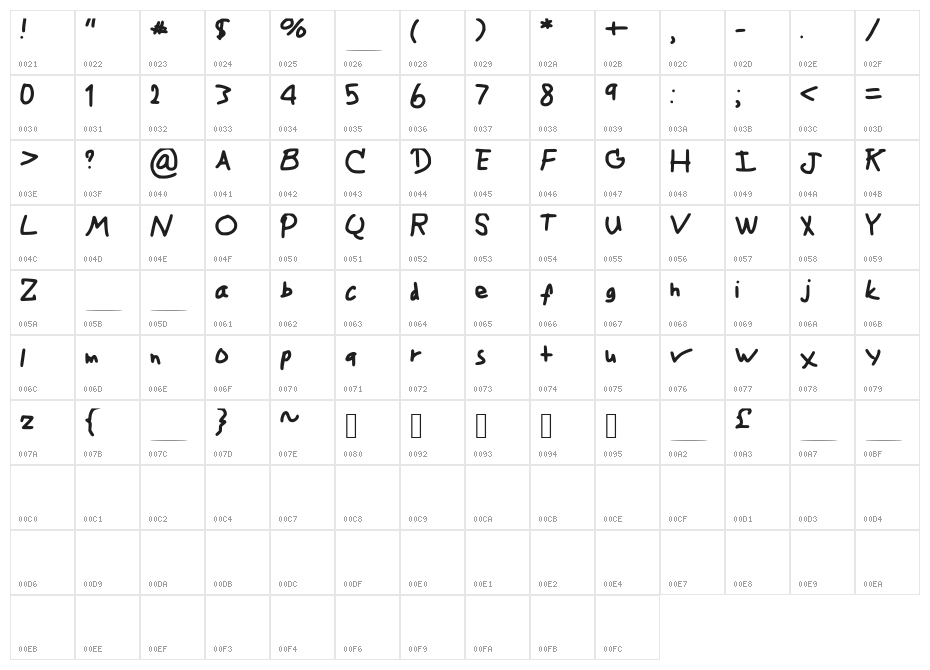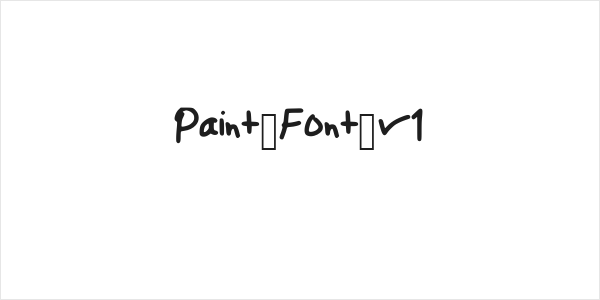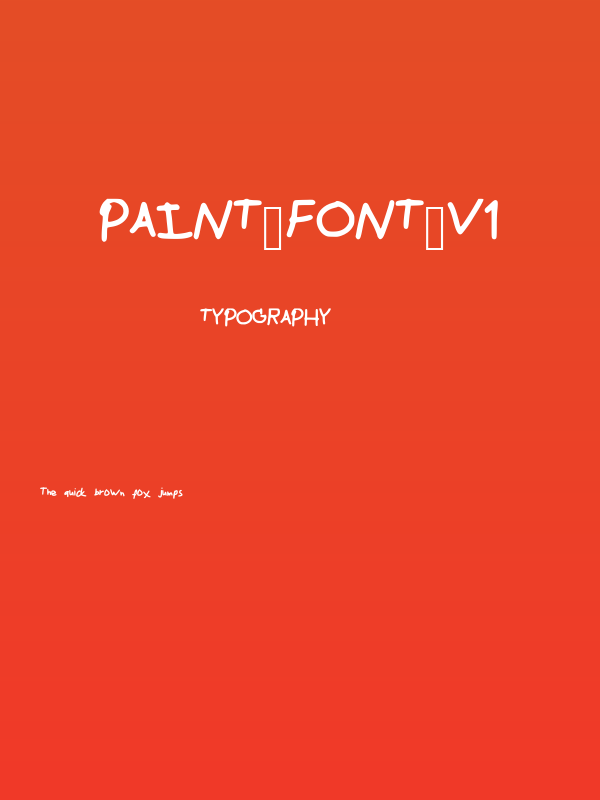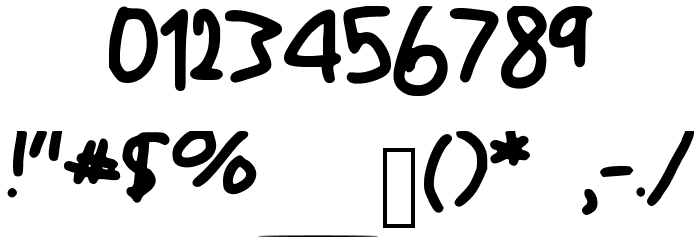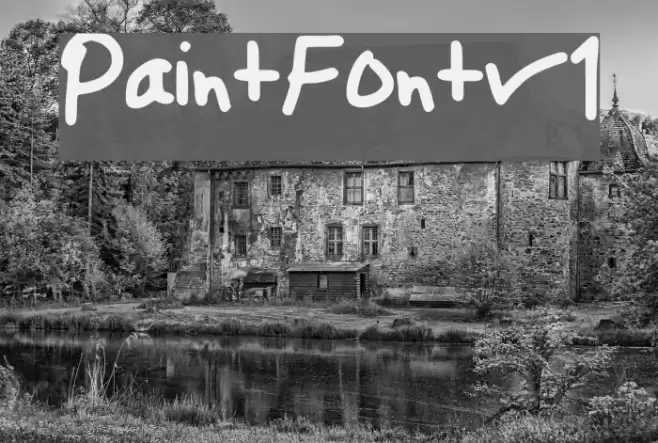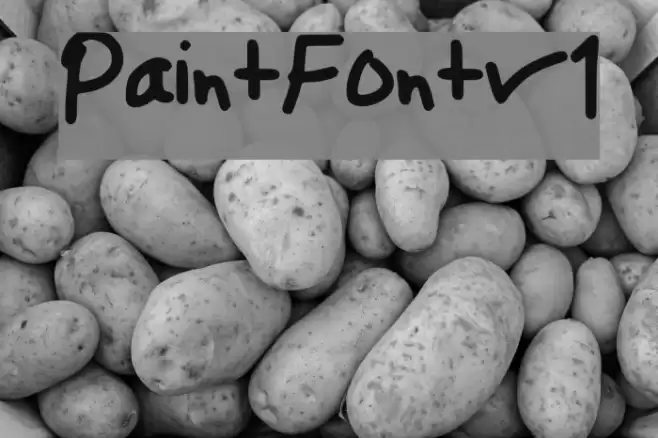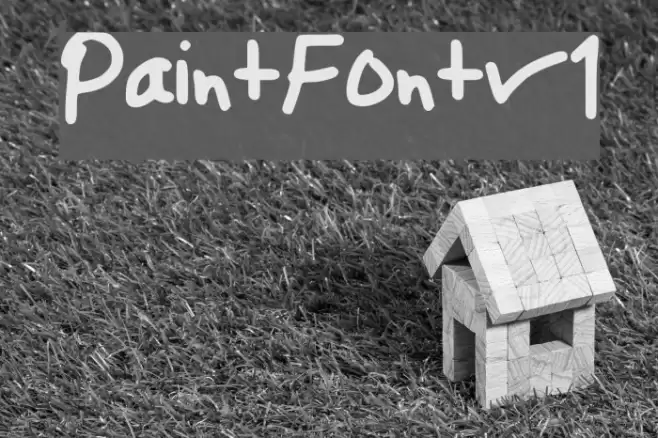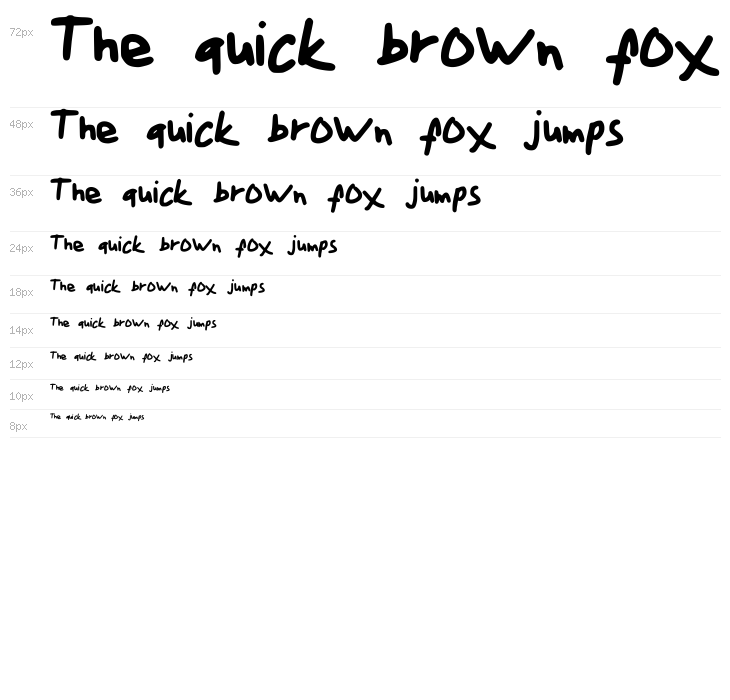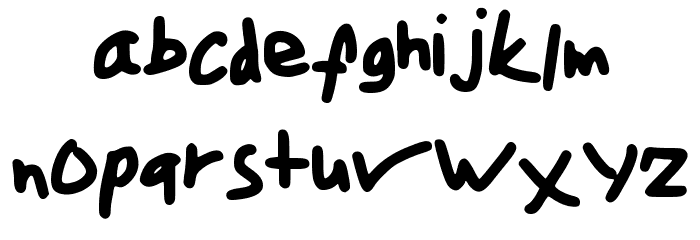
Paint_Font_v1 Font
| 全体的なスタイル | Casual |
| 用途 | Headlines, Logos, Informal Text |
| おすすめプロジェクト | Ideal for children's books, greeting cards, playful branding, and informal invitations. |